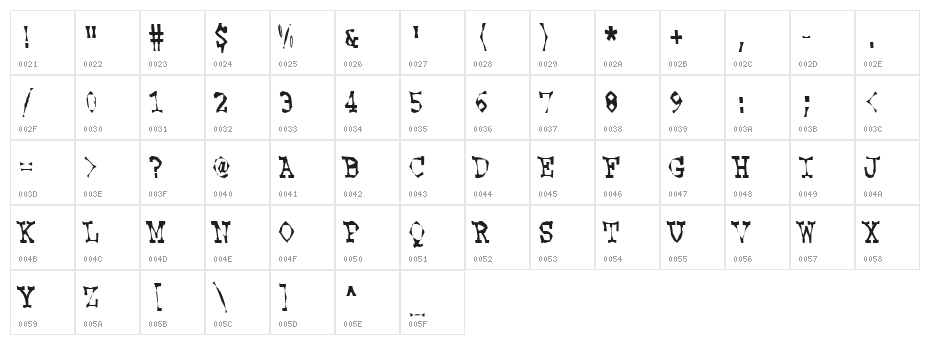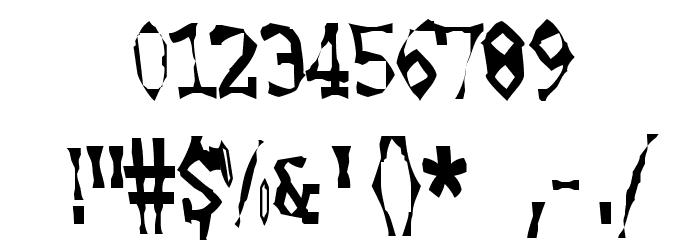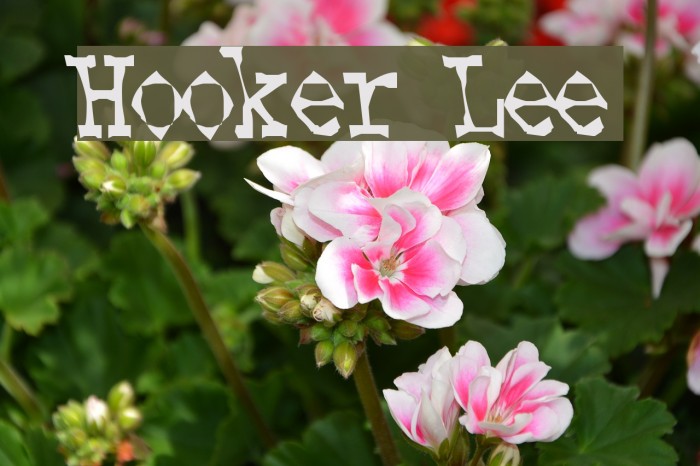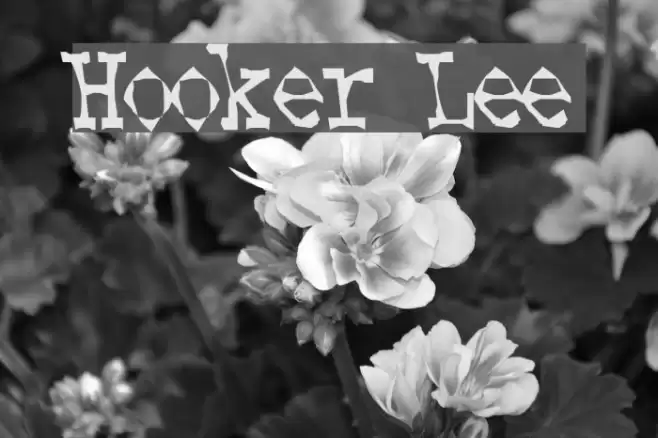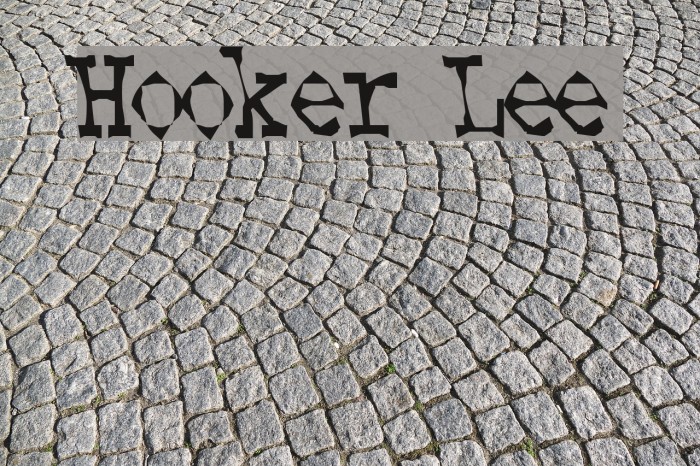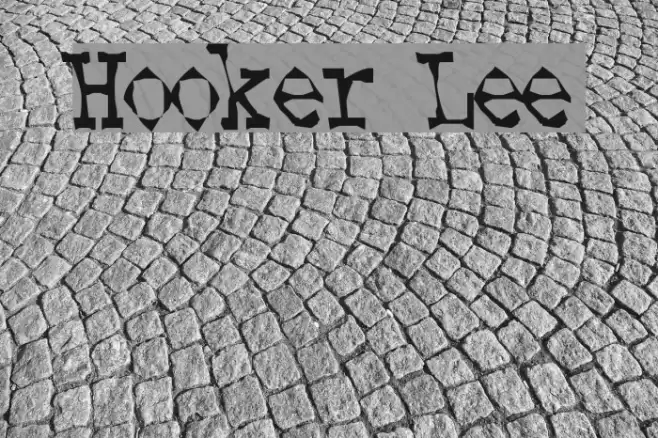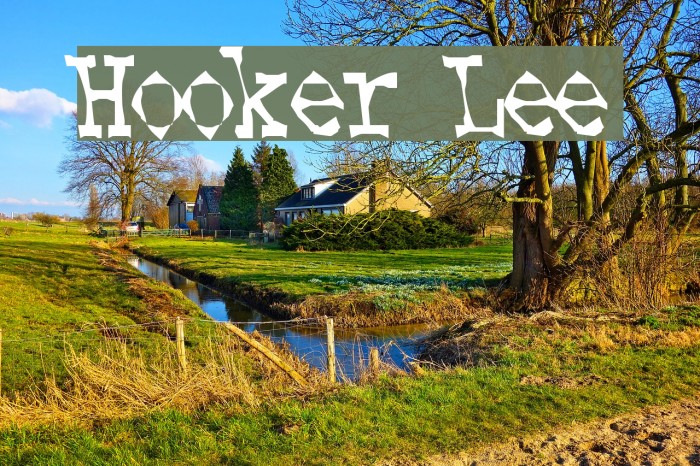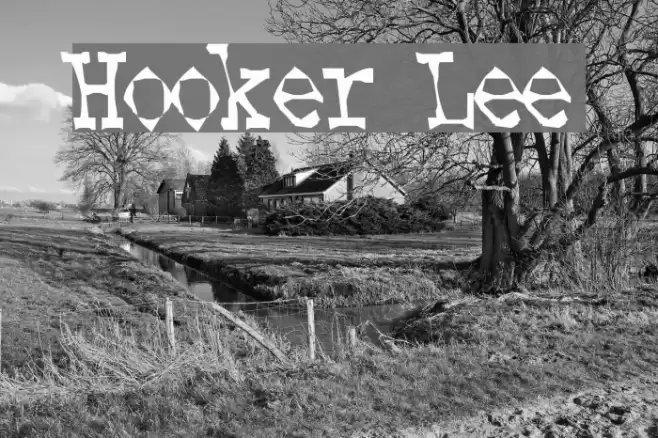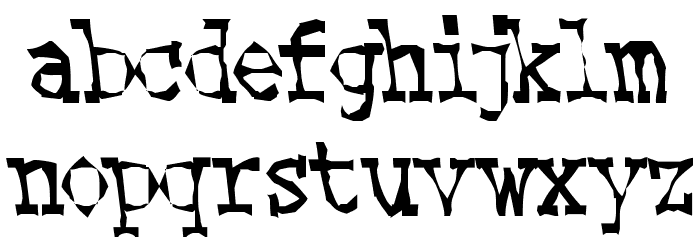
Hooker Lee Font
✎ Typewriter
| Vorgeschlagene Projekte | Ideal for horror-themed designs, edgy posters, album covers, and any project requiring a dramatic, unconventional typeface. |